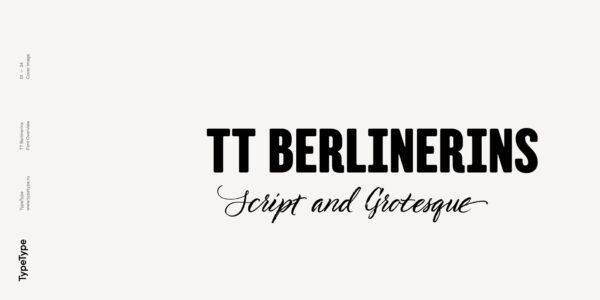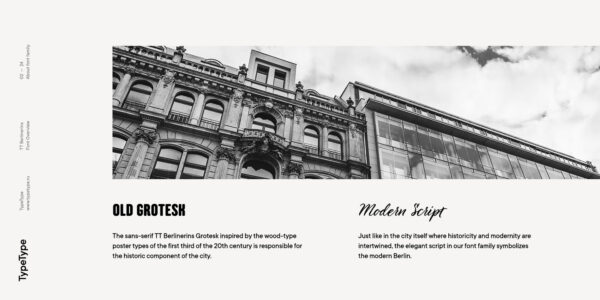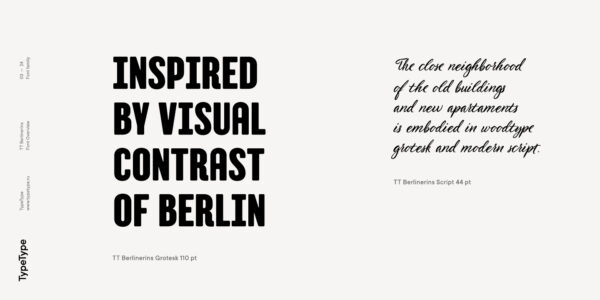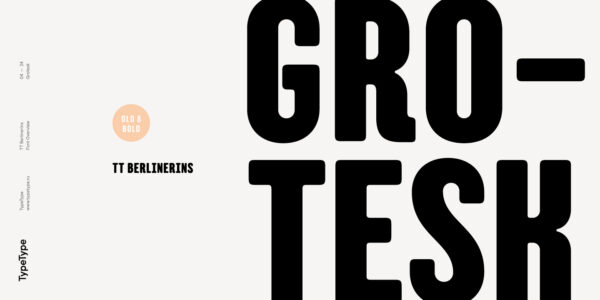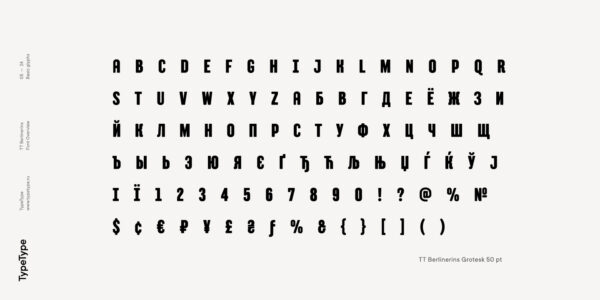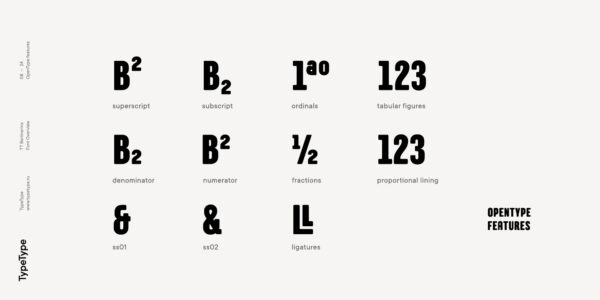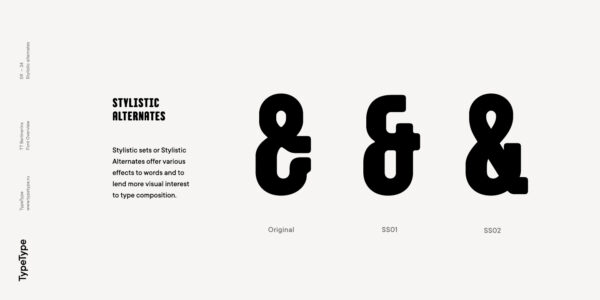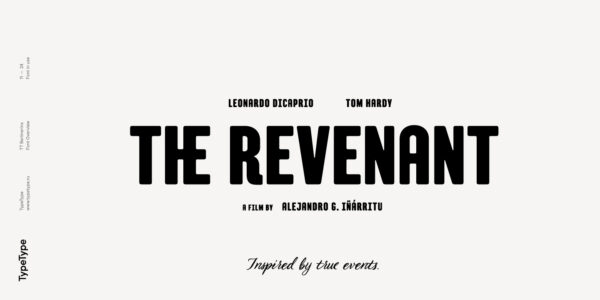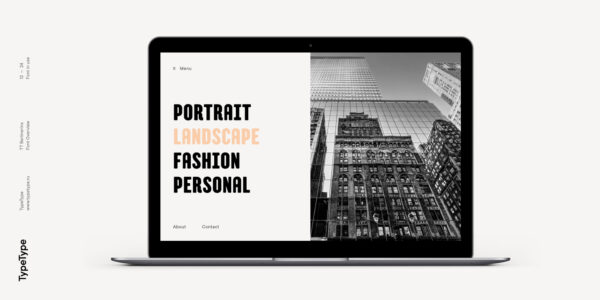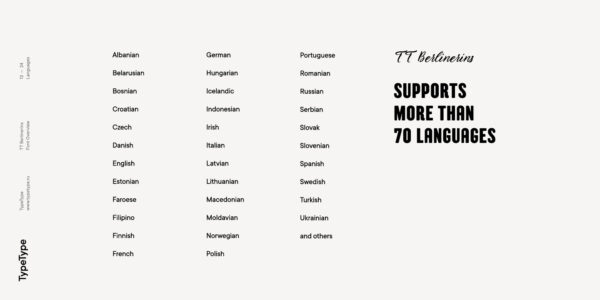
TT Berlinerins
TT Berlinerins — ТТ Берлинеринс
Произносится «ТТ Берлинеринс». «Berlinerins» — производное слово от Berlinerin, в переводе с немецкого «жительница Берлина». Буквы «TT» являются аббревиатурой названия компании.
TT Berlinerins — это контрастная пара шрифтов, посвящённая Берлину. Элегантный скрипт символизирует современный город, а гротеск отвечает за его историческую составляющую.
О гарнитуре TT Berlinerins
TT Berlinerins — это контрастная пара шрифтов, которая по сути является нашим трибьютом Берлину. Также, как и в самом городе переплетаются историчность и современность, так и в нашем шрифтовом семействе элегантный скрипт символизирует собой современный Берлин, а гротеск, выполненный в стиле плакатных wood-type шрифтов первой трети 20-го века, отвечает за историческую составляющую города.
Идея данного проекта появилась в начале 2016 года, когда мы познакомились с Берлинским каллиграфом Евгенией Пестовой, которая поделилась с нами современным видением каллиграфии и впечатлениями от города. Wood-type гротеск появился позже, после посещения другим нашим коллегой Берлина и удивительным рассказом об увиденном. Город насыщен контрастами, он одновременно и современный, и очень раритетный. Фотографии и впечатления от поездки также легли в основу нашего проекта. Таким образом мы добавили немного грубости и неравномерности от старого Берлина.
TT Berlinerins Script содержит в себе 998 глифов, включая более 240 росчерков для которых мы прописали специальную фичу. В TT Berlinerins Script мы также нарисовали большое количество лигатур и интегрировали широкую поддержку OpenType features: ordn, frac, case, sups, sinf, numr, dnom, tnum, pnum, calt, liga.
TT Berlinerins Grotesk содержит только прописные буквы, включает в свой кассовый состав несколько декоративных лигатур, а также широкую поддержку OpenType фич: ordn, frac, sups, sinf, numr, dnom, tnum, pnum, liga, salt and two stylistic sets ss01, ss02 for the ampersand.
liga | Standard Ligatures
the ff
frac | Fractions
1/2 1/4
ss01 | Stylistic Set 1
&